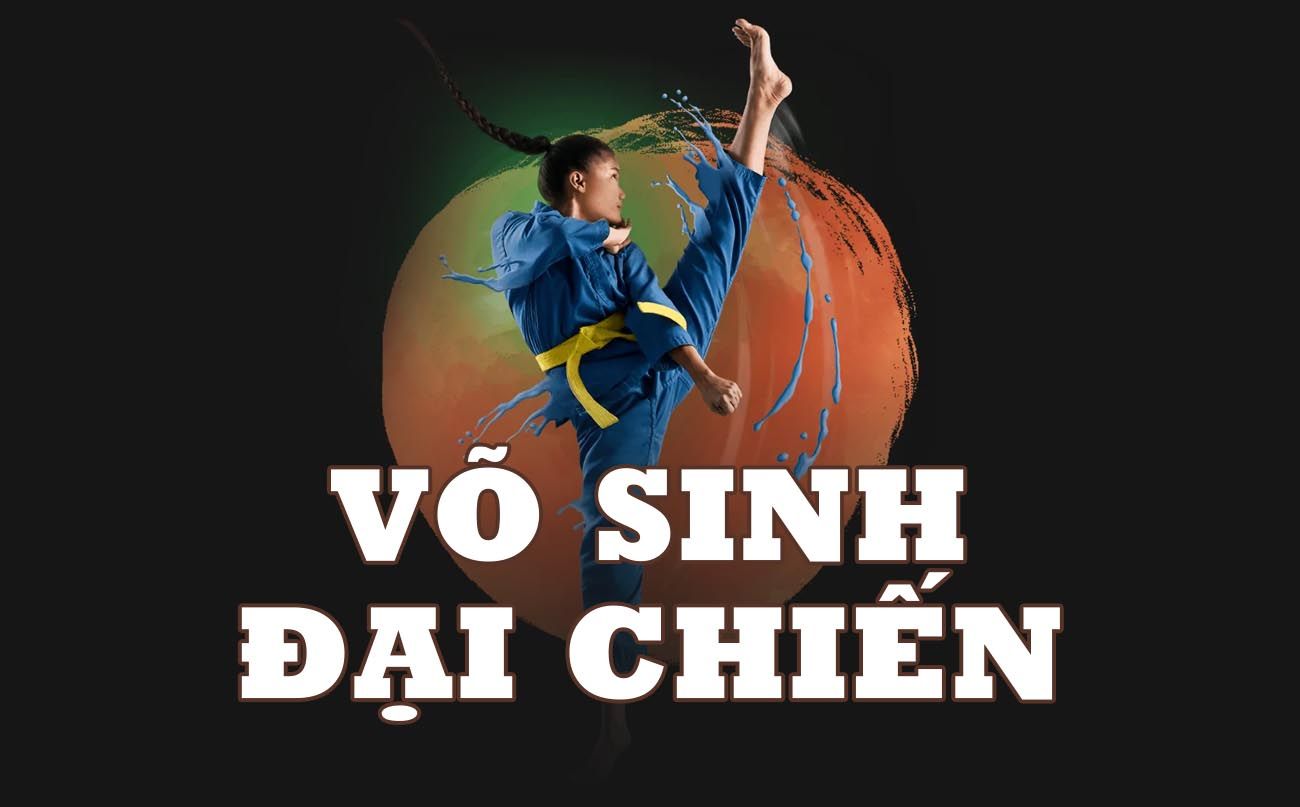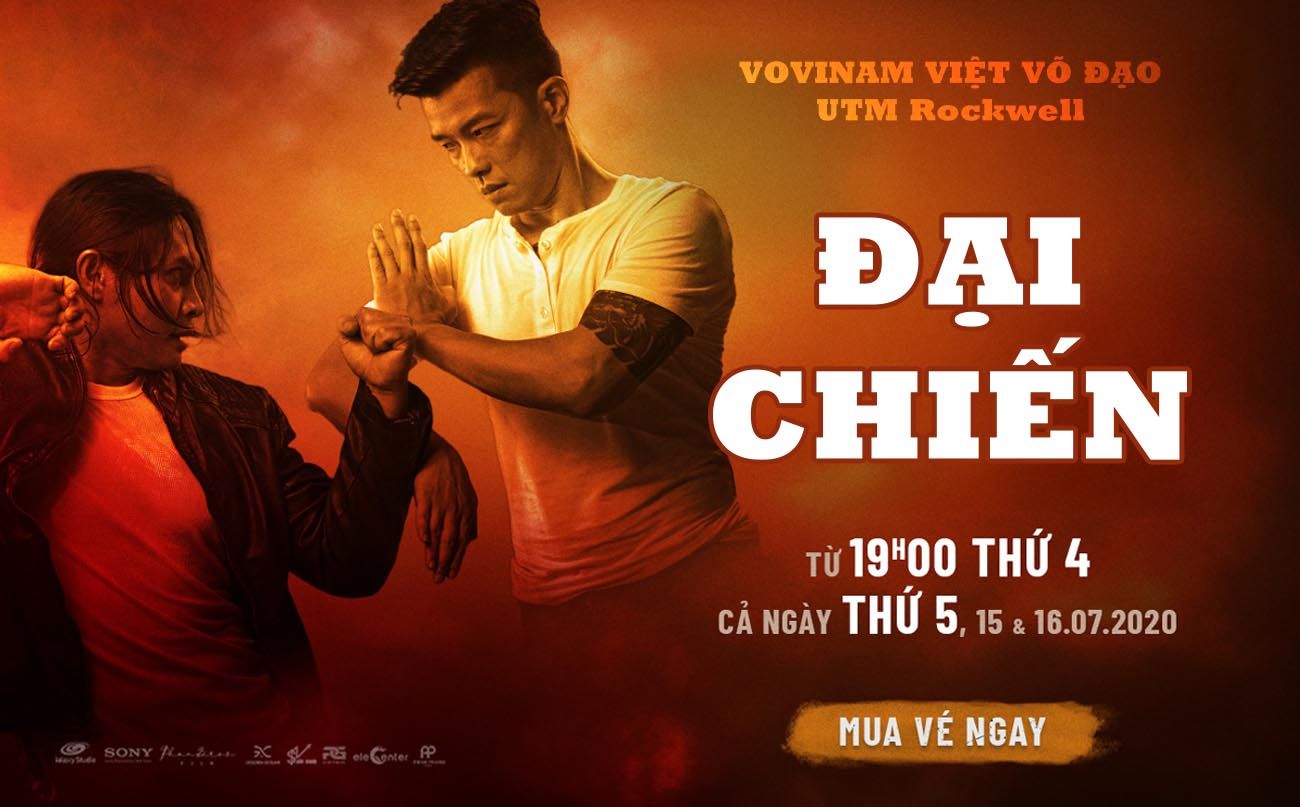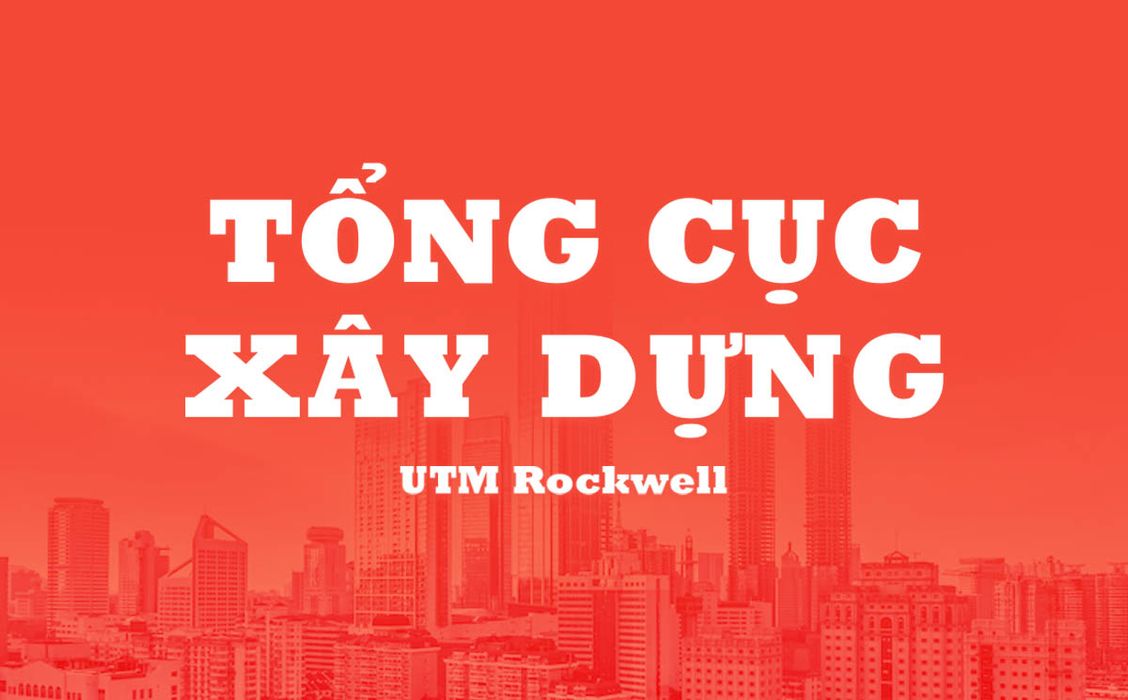
Bạn đang tìm một font chữ serif có thiết kế chắc chắn, dễ đọc và mang phong cách cổ điển? Font UTM Rockwell chính là lựa chọn lý tưởng. Đây là bản Việt hóa hoàn chỉnh của font Rockwell – một trong những kiểu chữ slab serif kinh điển nhất trong lịch sử thiết kế đồ họa.
UTM Rockwell là phiên bản font chữ được Việt hóa từ nguyên mẫu Rockwell (Monotype, 1934), thuộc nhóm slab serif với các chân chữ hình vuông đặc trưng. Bộ font này được nhóm UTM (Urban Type Management) Việt hóa, bổ sung đầy đủ dấu tiếng Việt, ký tự đặc biệt và giữ nguyên cấu trúc ổn định của bản gốc.
Font UTM Rockwell sở hữu chân chữ vuông và dày, mang lại cảm giác vững chắc, rõ ràng và dễ đọc trong mọi hoàn cảnh sử dụng. Thiết kế cân đối, với tỉ lệ hoàn hảo giữa các nét dọc và ngang, giúp font hoạt động hiệu quả ngay cả khi được dùng ở kích cỡ lớn. Đặc biệt, font hỗ trợ tiếng Việt đầy đủ, bao gồm đầy đủ dấu thanh, chữ hoa, chữ thường, tạo sự thuận tiện cho các nhà thiết kế khi ứng dụng vào các sản phẩm nội địa. Ngoài ra, bộ font bao gồm các định dạng phổ biến như Regular, Bold và Italic, giúp tăng tính linh hoạt trong việc xây dựng hệ thống nhận diện thương hiệu hay thiết kế in ấn chuyên nghiệp.
Font chữ này rất phù hợp để sử dụng trong các thiết kế tiêu đề trang trọng như bìa sách, poster phim, banner quảng cáo. Trong lĩnh vực in ấn và xuất bản, UTM Rockwell phát huy thế mạnh khi được dùng cho báo chí, tạp chí hay tài liệu doanh nghiệp. Font cũng là lựa chọn lý tưởng để thiết kế logo thương hiệu, đặc biệt trong các ngành mang tính truyền thống như giáo dục, luật pháp hay bảo hiểm. Không chỉ vậy, khi dùng trong trình bày slide hay infographics, UTM Rockwell giúp tăng tính chuyên nghiệp và đảm bảo sự rõ ràng cho nội dung trình bày.
Với thiết kế mạnh mẽ, dễ đọc và hỗ trợ tiếng Việt đầy đủ, font UTM Rockwell là lựa chọn không thể bỏ qua nếu bạn đang tìm kiếm một phông chữ serif Việt hóa vừa cổ điển vừa hiện đại. Hãy tải ngay để áp dụng vào các dự án thiết kế chuyên nghiệp của bạn!